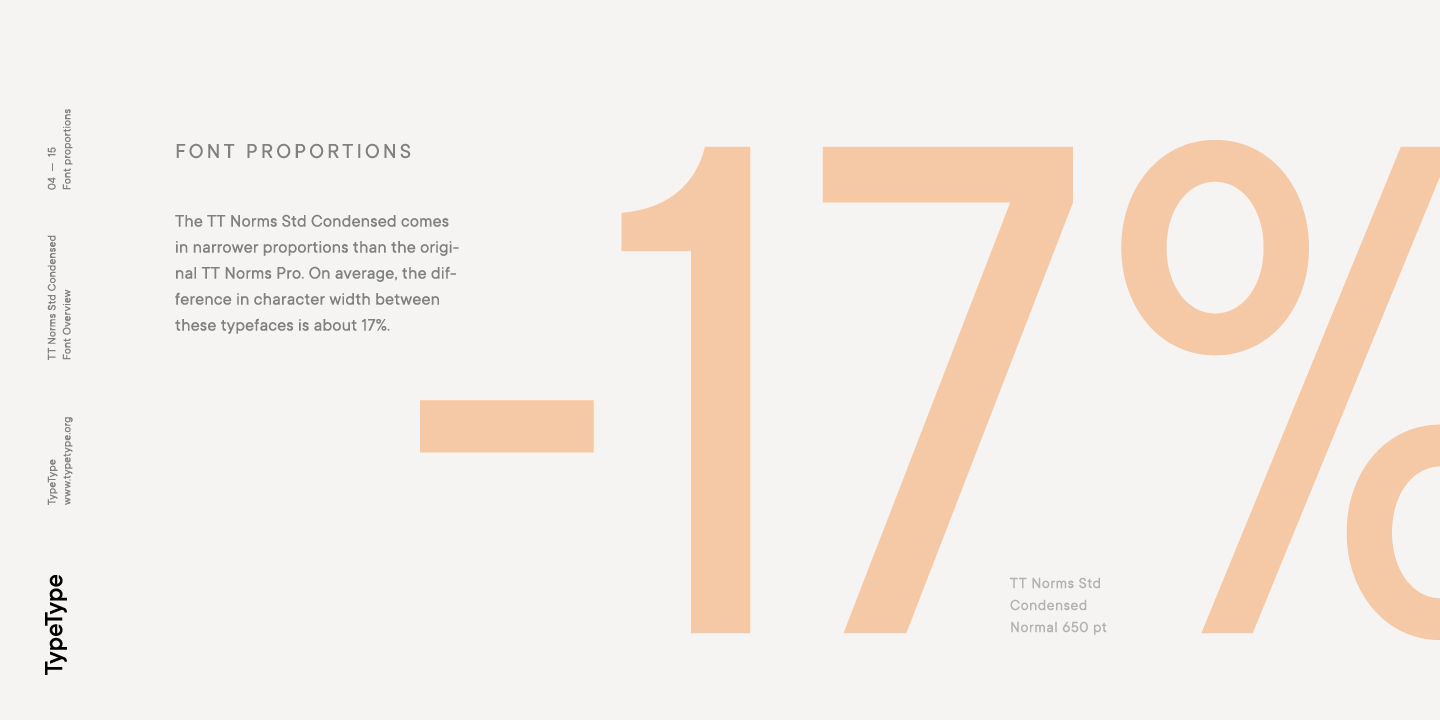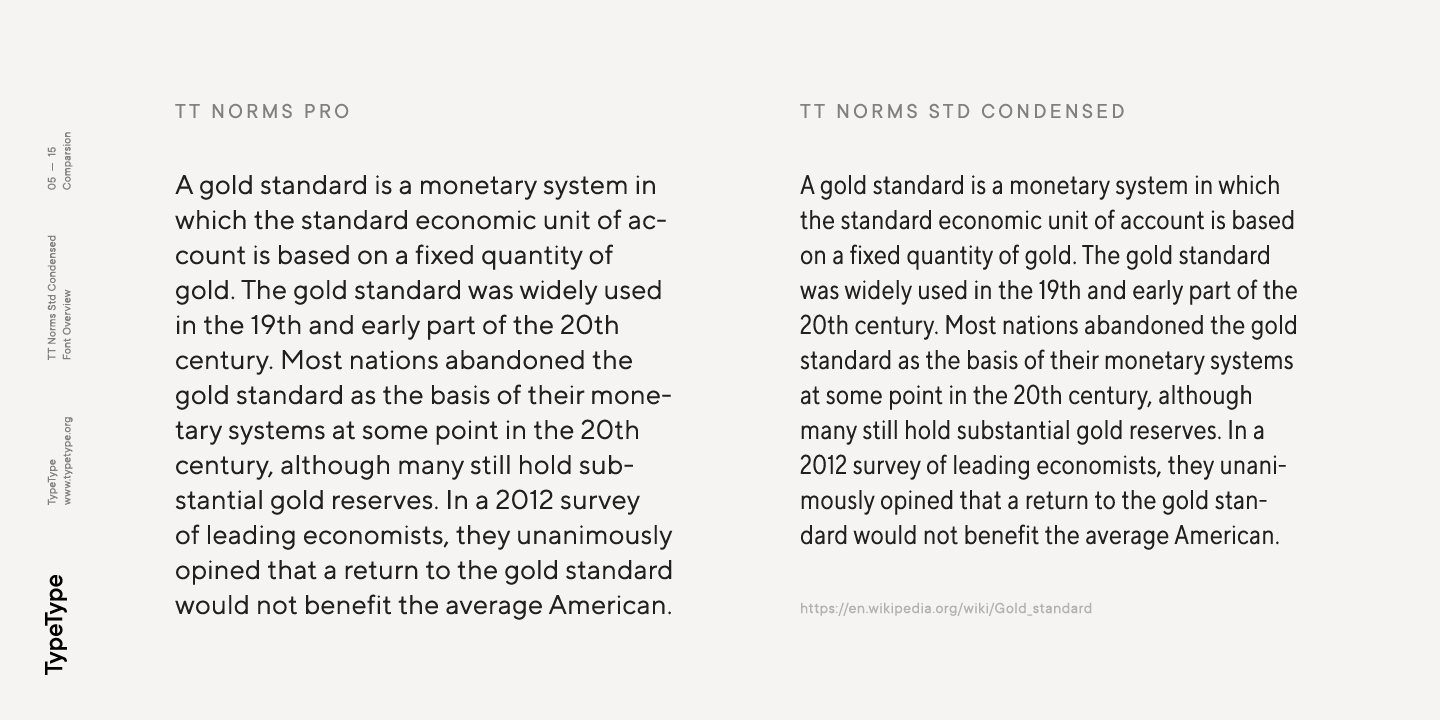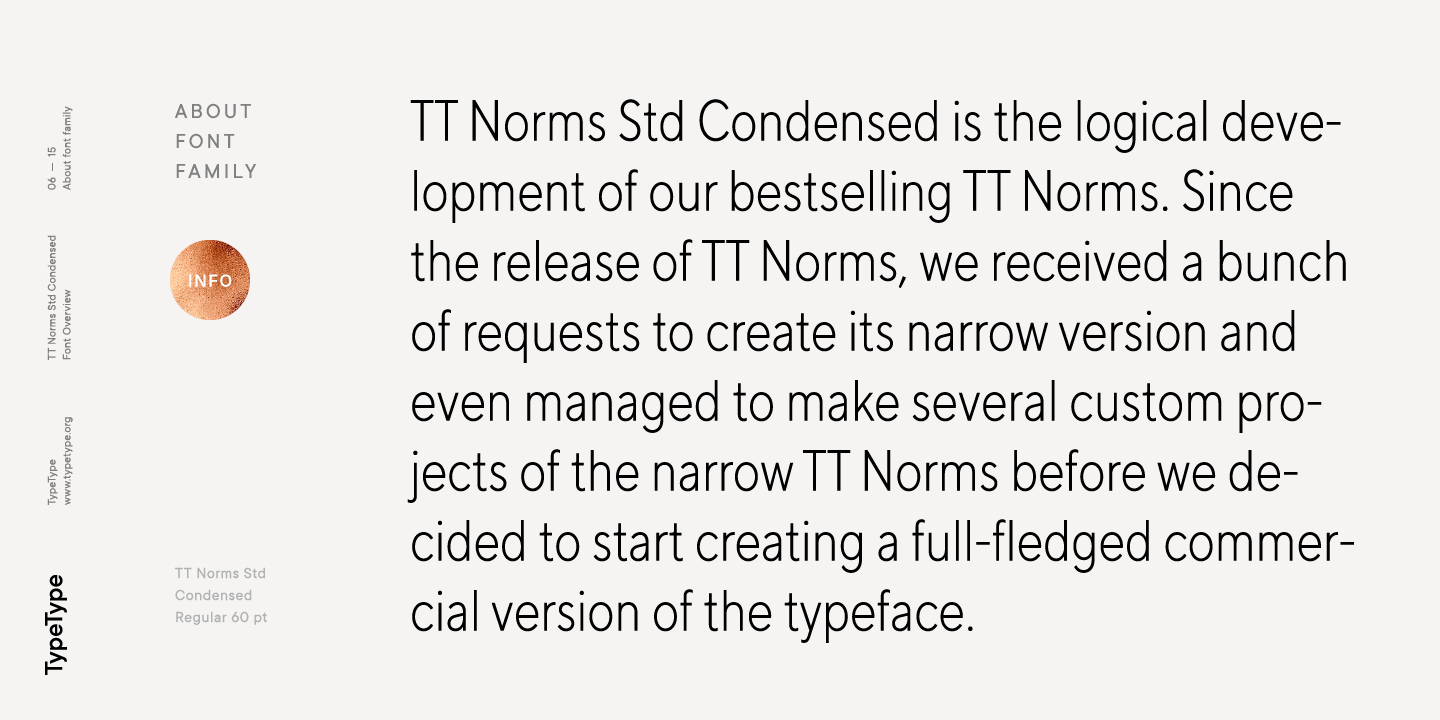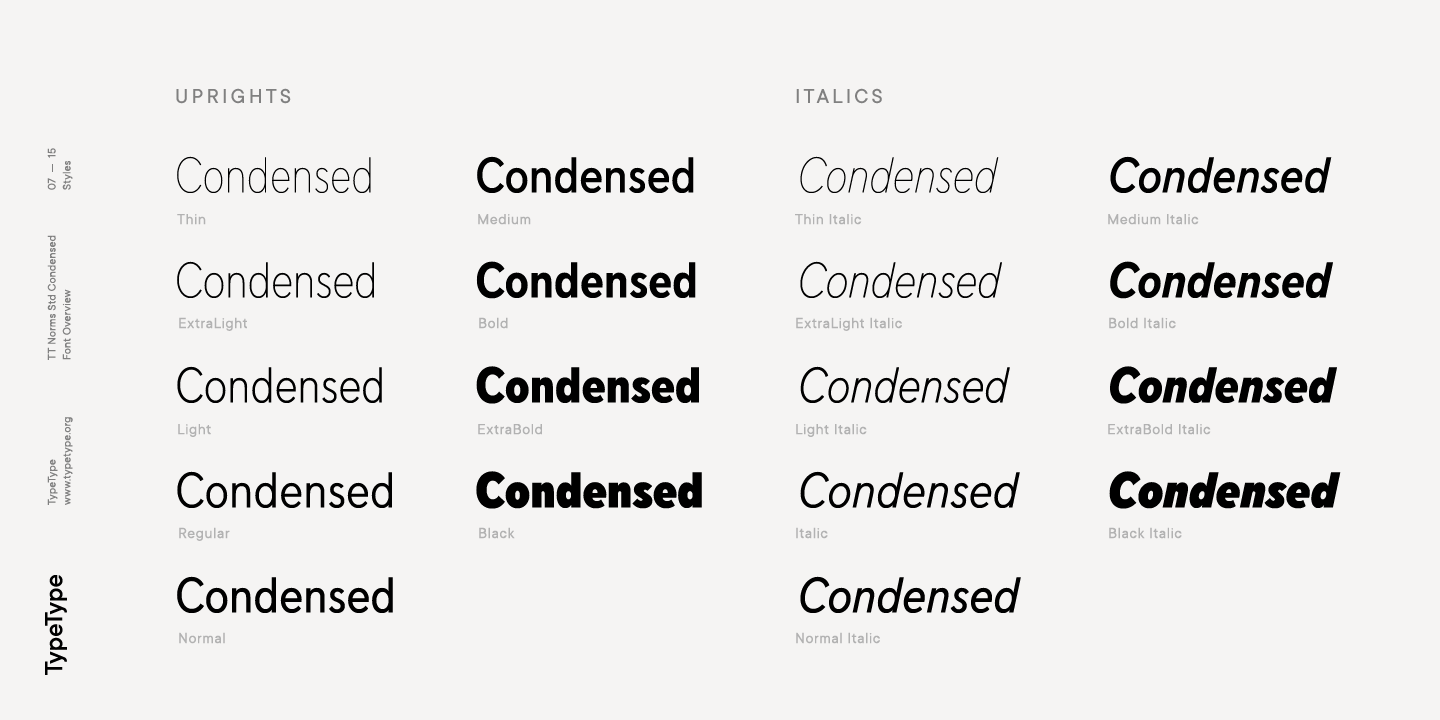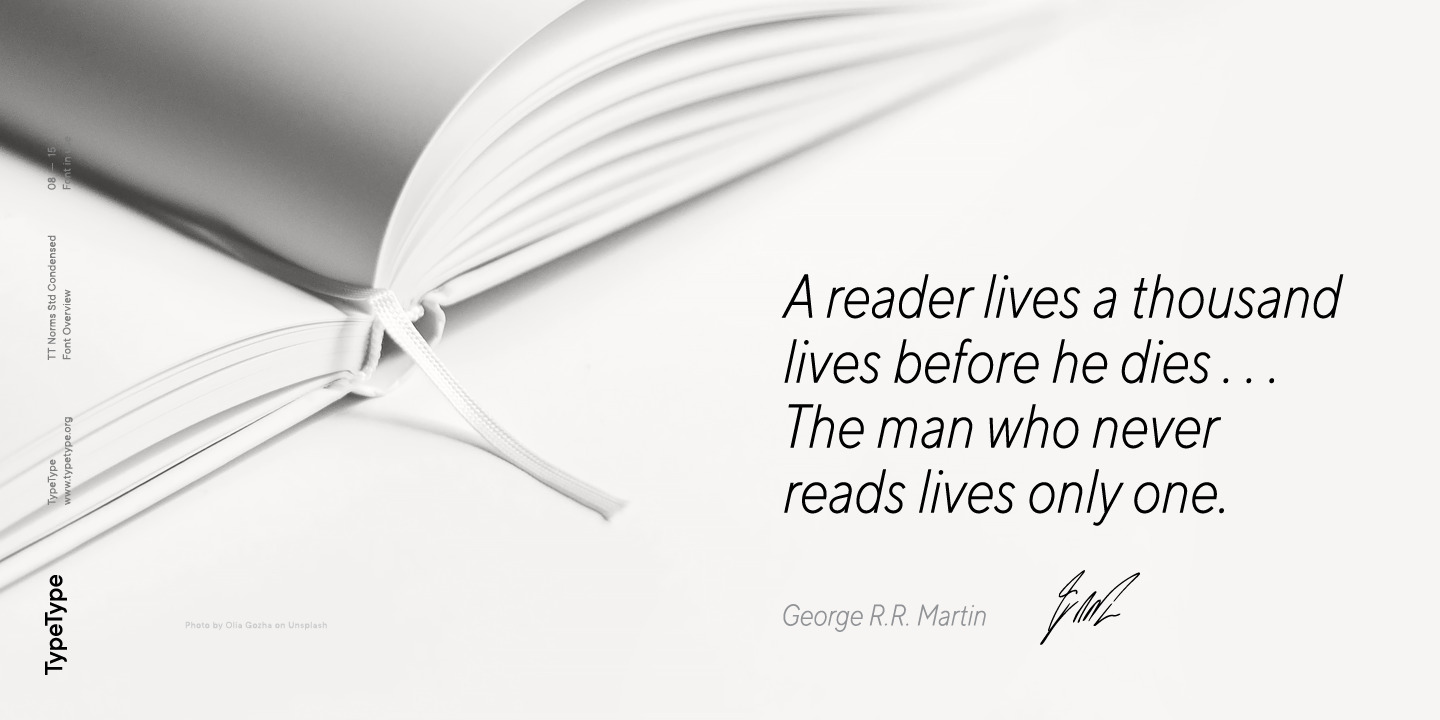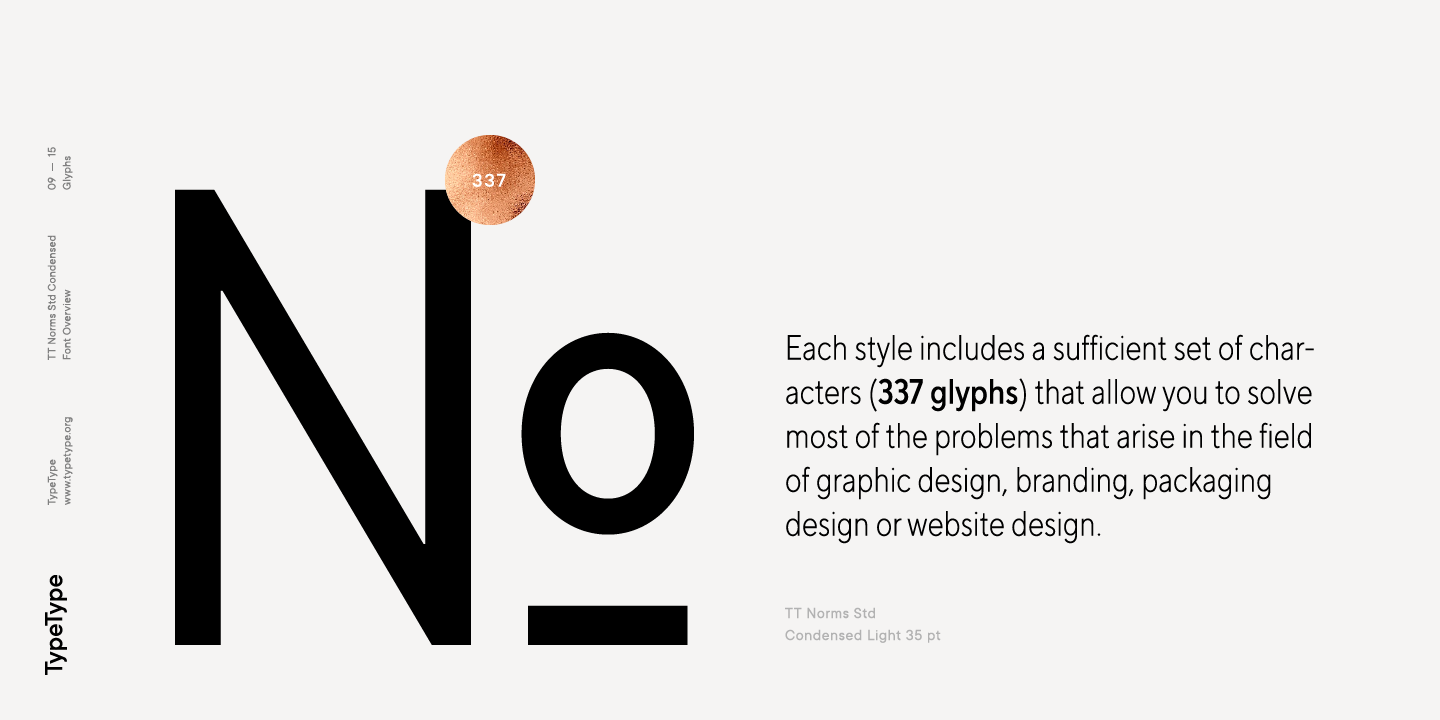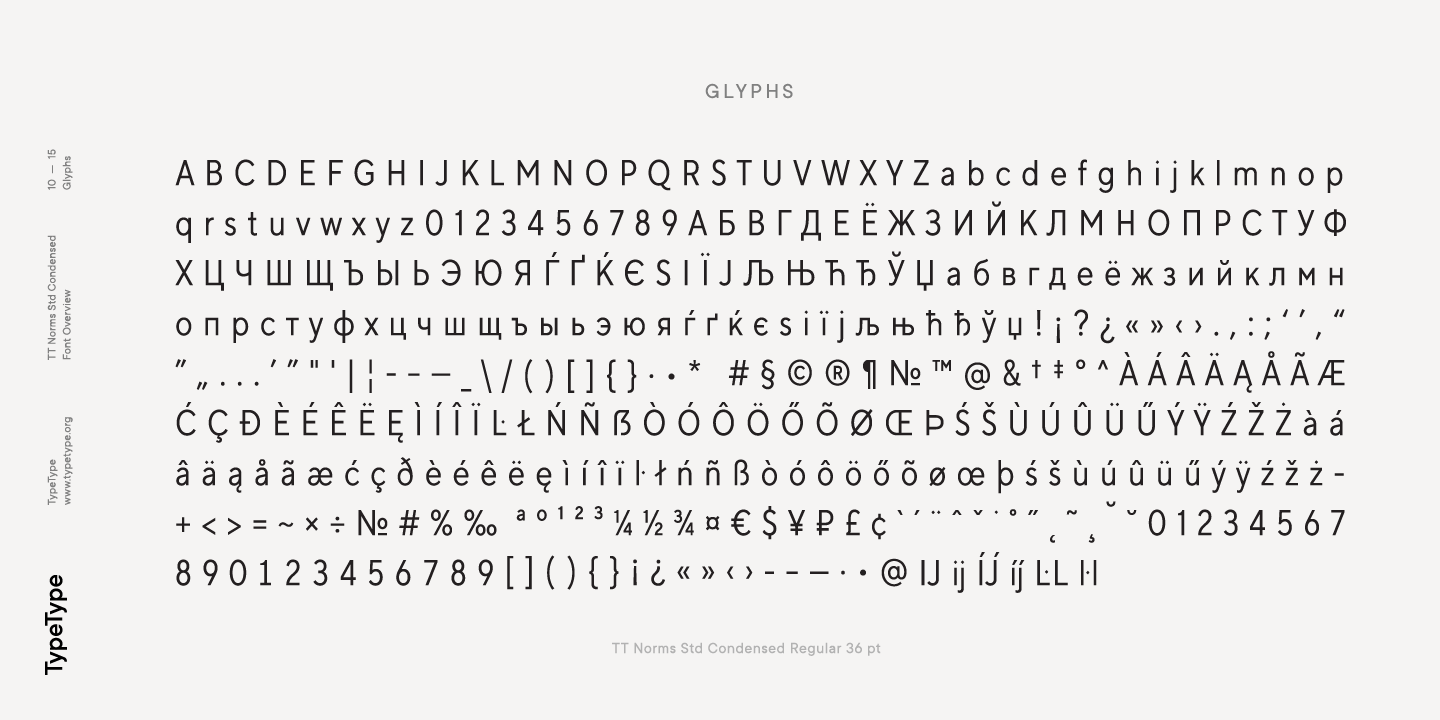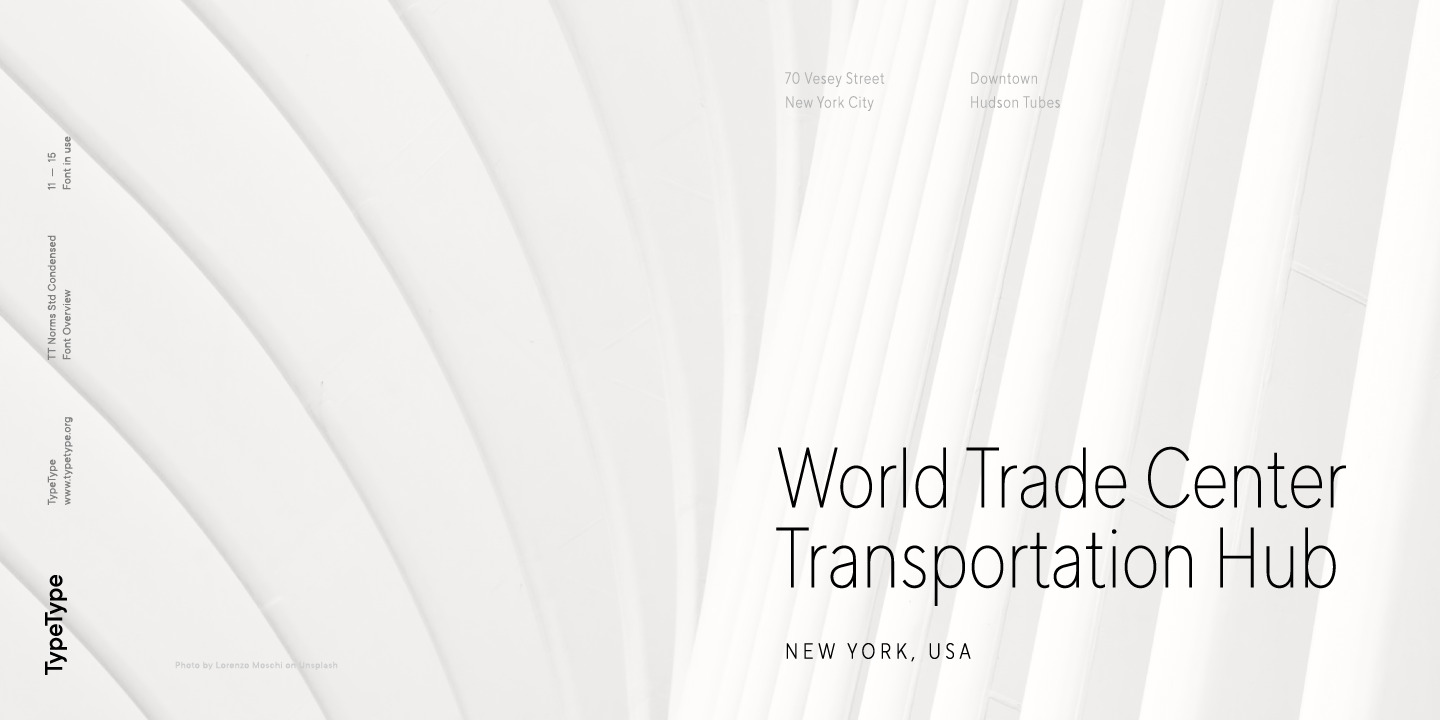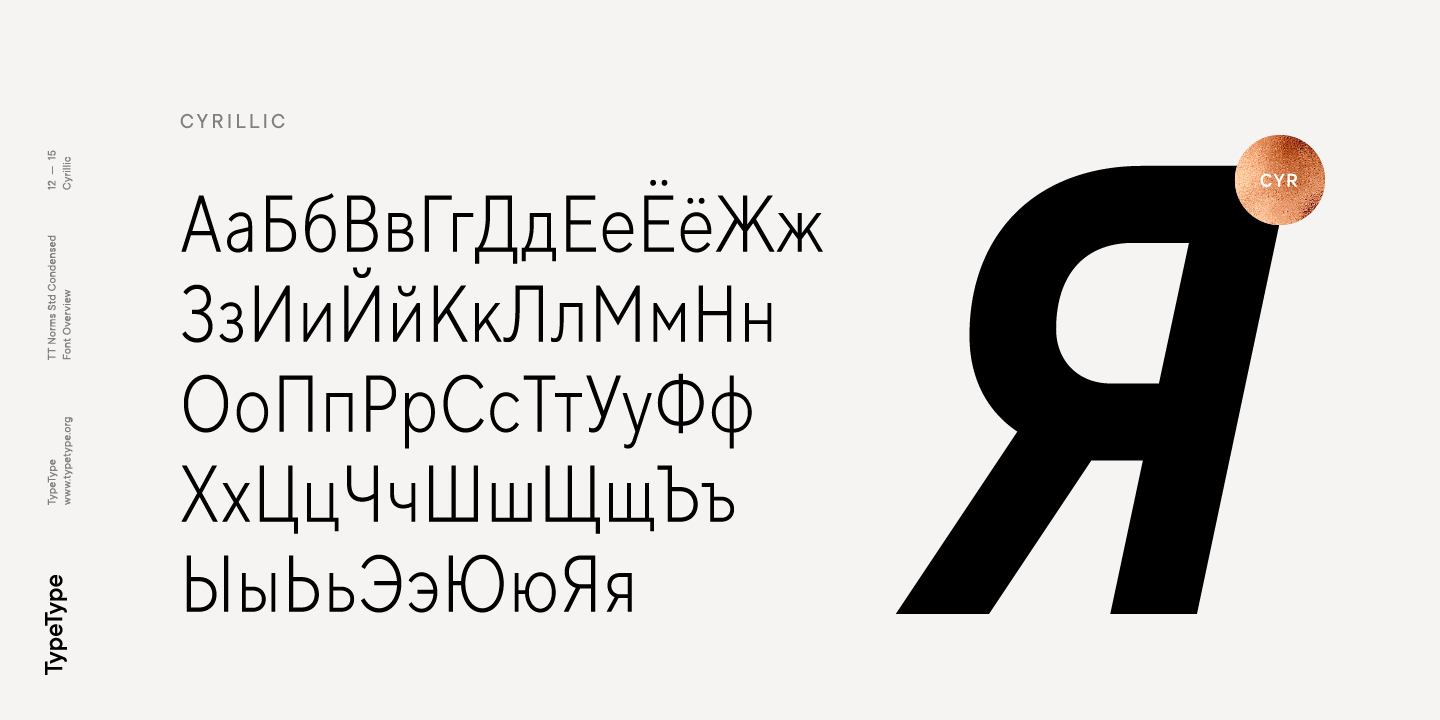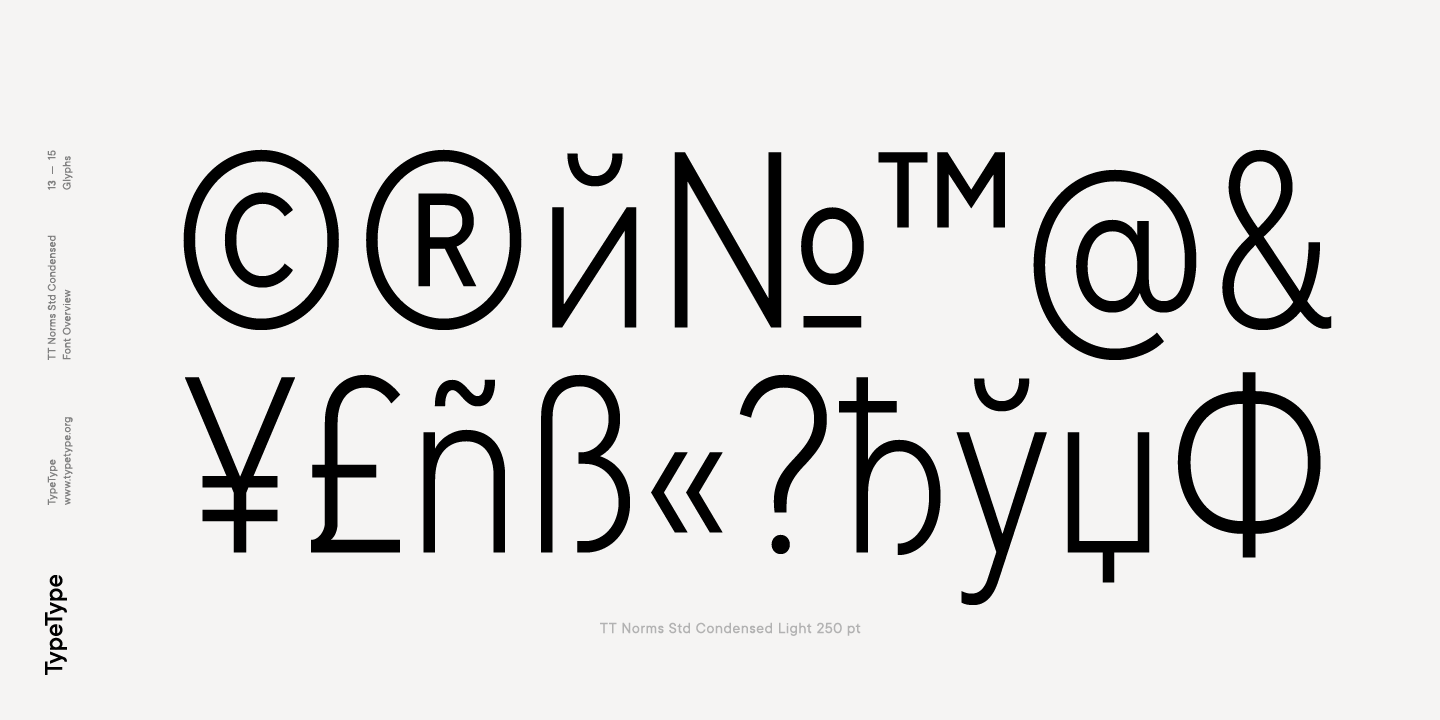
TT Norms® Std Condensed
TT Norms® Std Condensed — النسخة الضيقة من الخط الأكثر مبيعًا TT Norms® Pro. لقد ورث الخط من "السلف" نسبه الكلاسيكية ومرونته في الاستخدام.
TT Norms Std Condensed has narrower proportions than the original family
TT Norms Std Condensed is the logical development of our bestselling TT Norms. Since the release of TT Norms, we received a bunch of requests to create its narrow version and even managed to make several custom projects of the narrow TT Norms before we decided to start creating a full-fledged commercial version of the typeface.
TT Norms® Std Condensed inherited the classic proportions of characters
The TT Norms Std Condensed font family consists of 18 faces (9 upright and 9 italics)
حول عائلة الخط TT Norms® Std Condensed
TT Norms Std Condensed هو تطور منطقي لنجاحنا الكبير TT Norms Pro. منذ إصدار TT Norms Pro، تلقينا العديد من الطلبات لإنشاء نسخة ضيقة منه، وقمنا حتى بإنجاز بعض المشاريع المخصصة لنسخة ضيقة من TT Norms Pro قبل أن نقرر البدء في إنشاء نسخة تجارية كاملة من الخط.
في بداية المشروع، أجرينا دراسة صغيرة واختبرنا عدة خيارات لعرض الخط. على الرغم من أن TT Norms Std Condensed يتمتع بنسب أضيق مقارنةً بالنسخة الأصلية، إلا أنه ورث نسب الأحرف الكلاسيكية، والاهتمام بالتفاصيل، والدقة في تصميم كل حرف في الخط.
مجموعة من الخطوط TT Norms Std Condensed تتكون من 18 نمطًا (9 أنماط مستقيمة و9 مائلة). يحتوي كل نمط على مجموعة كافية من الرموز التي تتيح حل معظم التحديات في مجالات التصميم الجرافيكي، والعلامات التجارية، وتصميم العبوات، وكذلك تصميم مواقع الويب.
ميزات OpenType
case | Case Sensitive
({[H]})
tnum | Tabular Figures
012
dlig | Discretionary Ligatures
1/2 3/4